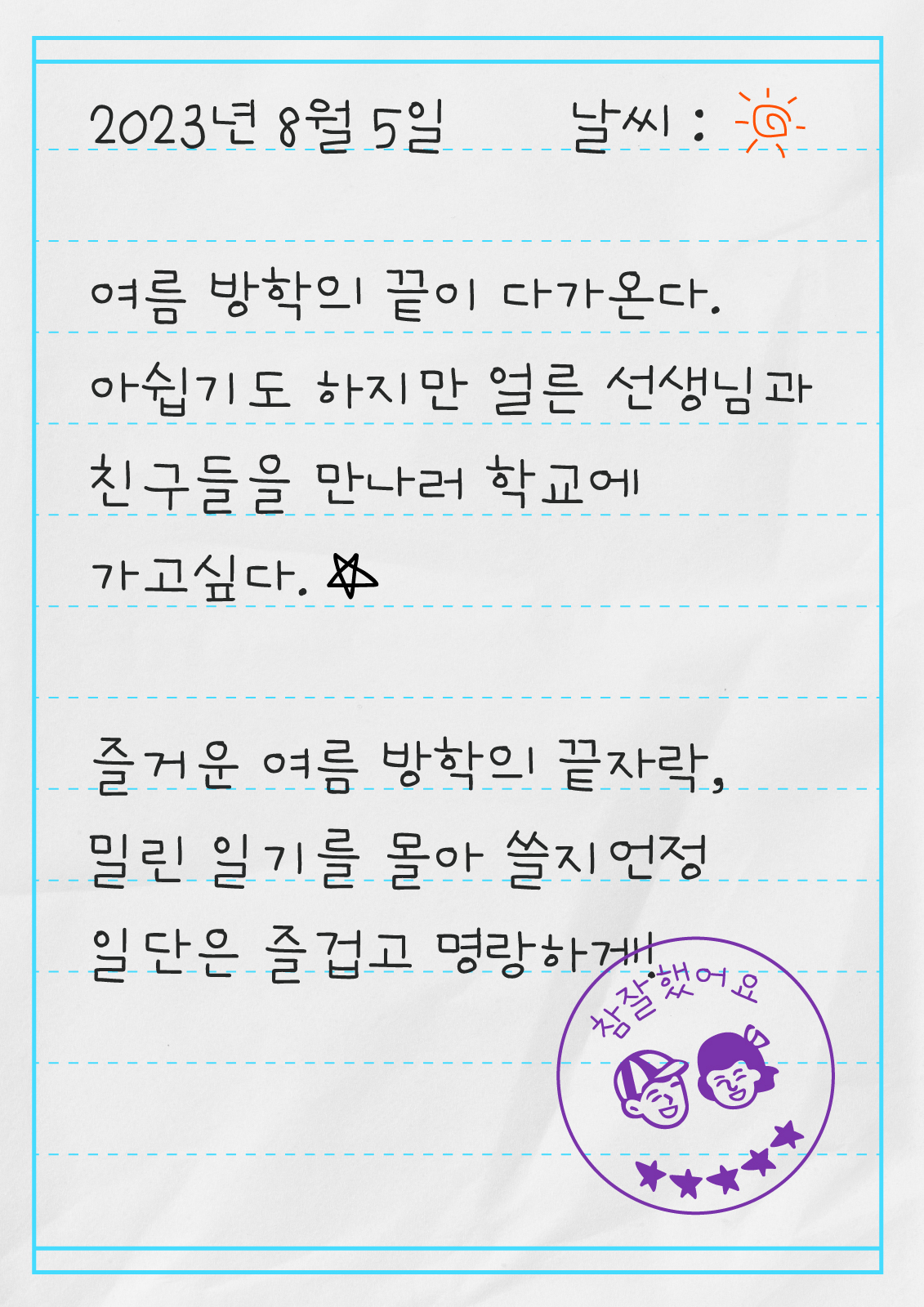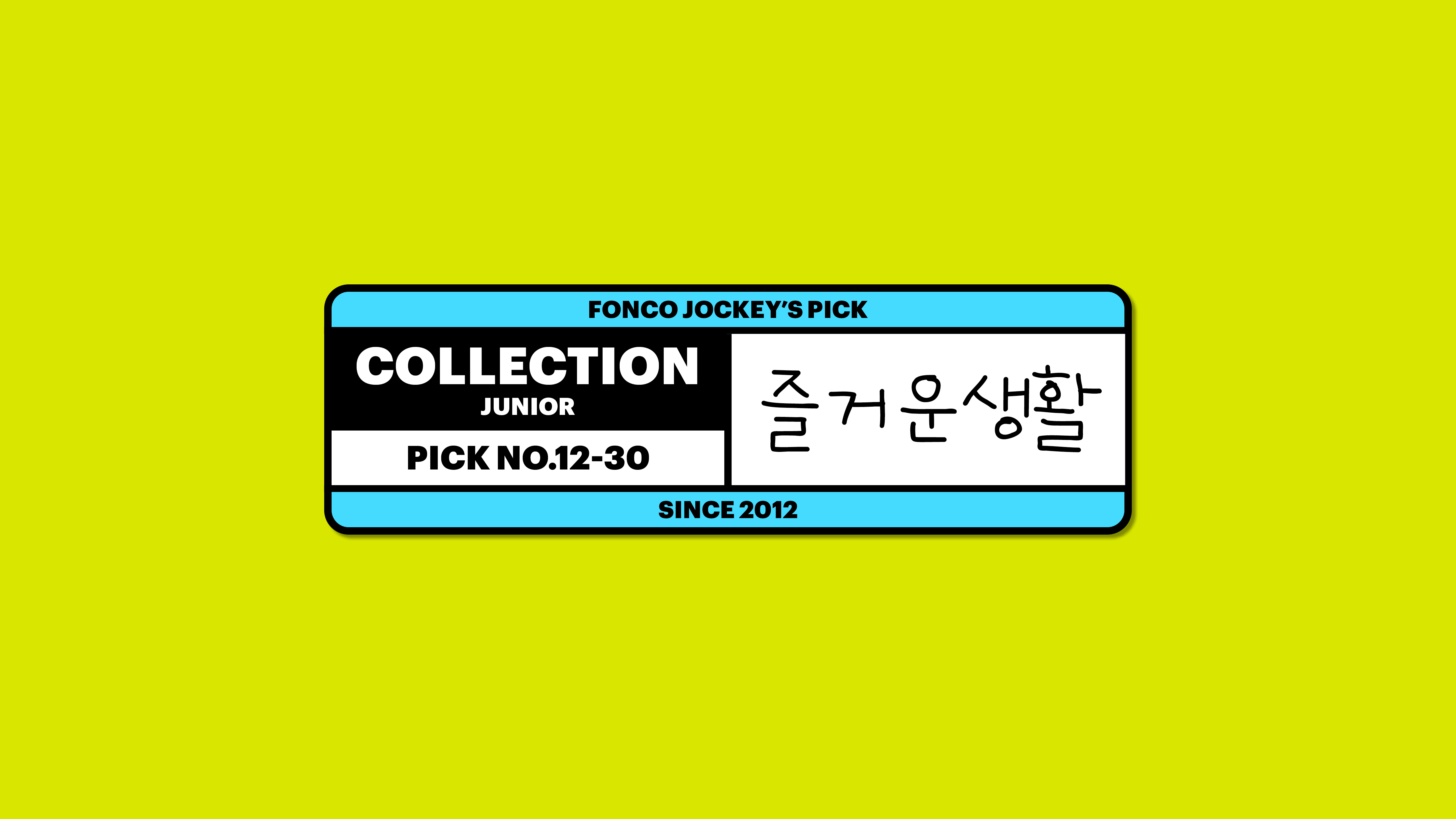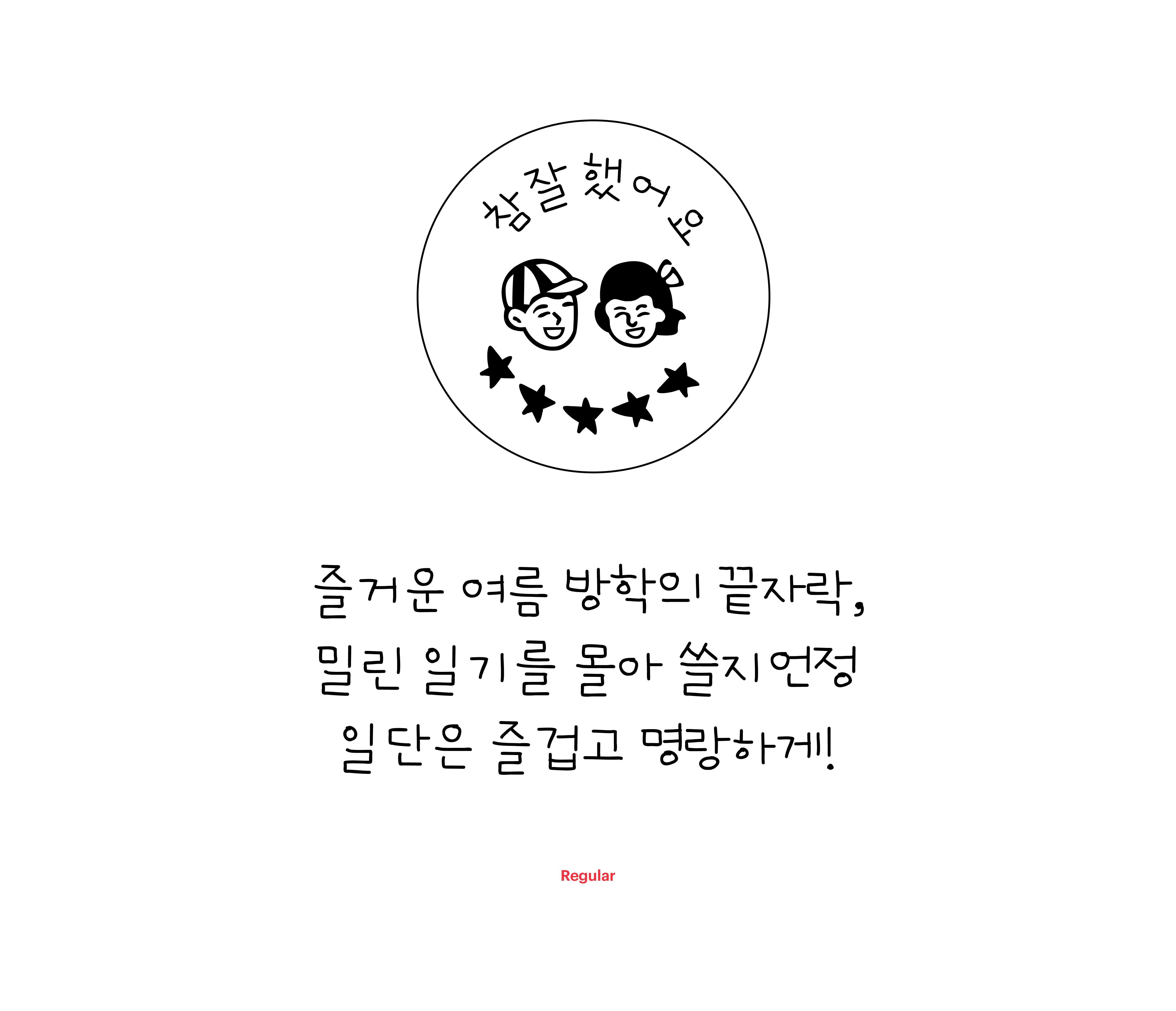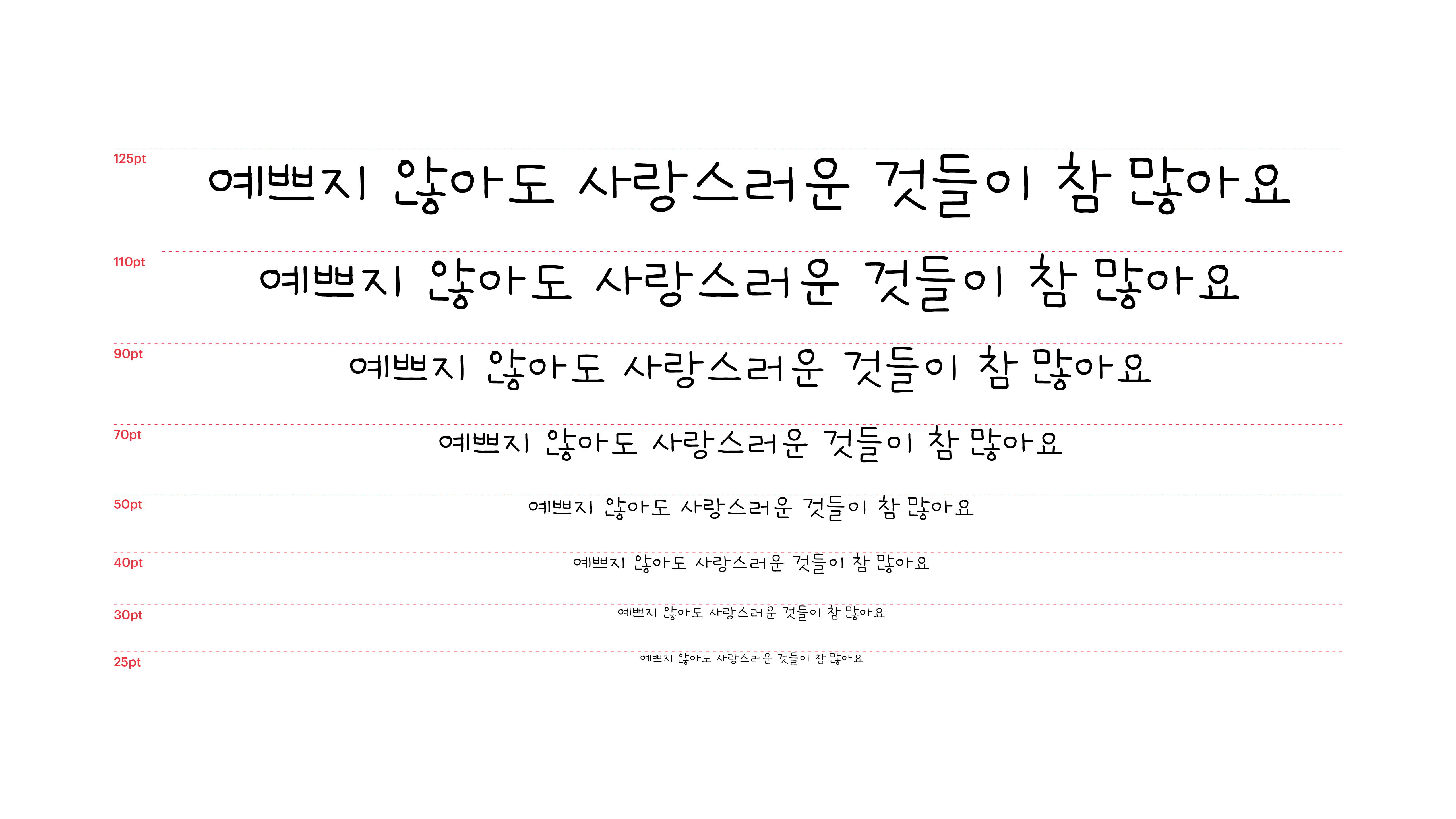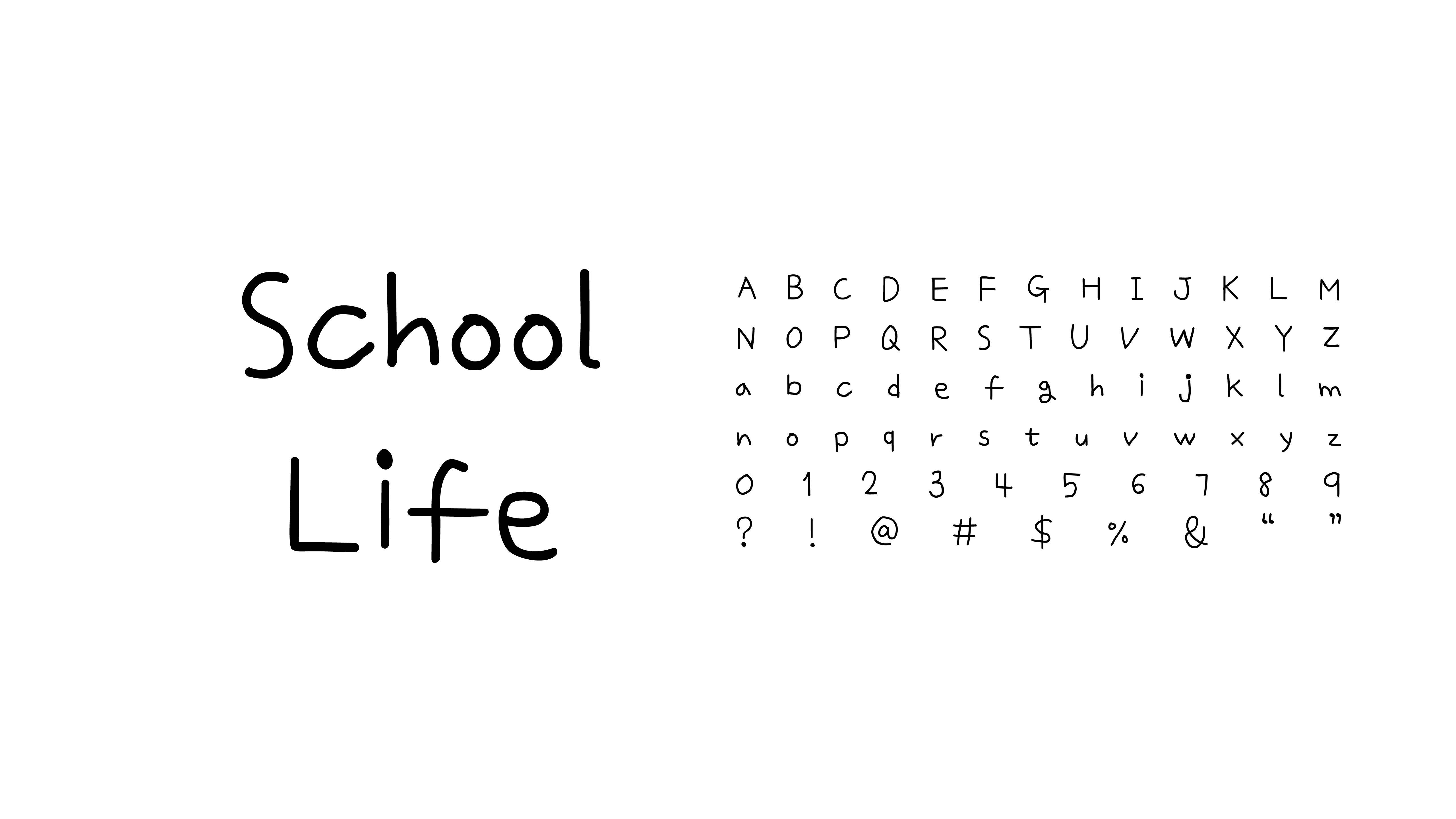
어른이 된 지금도 매일 일기 쓰기가 쉽지 않은데, 어린이들에게 그런 숙제는 너무 가혹했던 것 아닐까요? 예나 지금이나 밀려 쓴 아이들의 방학 일기장은 해맑기만 합니다. 자간이 일정하지도 않고 글자 중심도 들쭉날쭉하지만 명랑하기 그지없는 이 폰트처럼 말이에요. 세상에는 예쁘지는 않지만 사랑스러운 것들이 참 많습니다. 그래서 선생님들도 밀려 쓴 걸 알면서도 화를 내지 않으셨던 거겠죠?
Yoon 즐거운생활